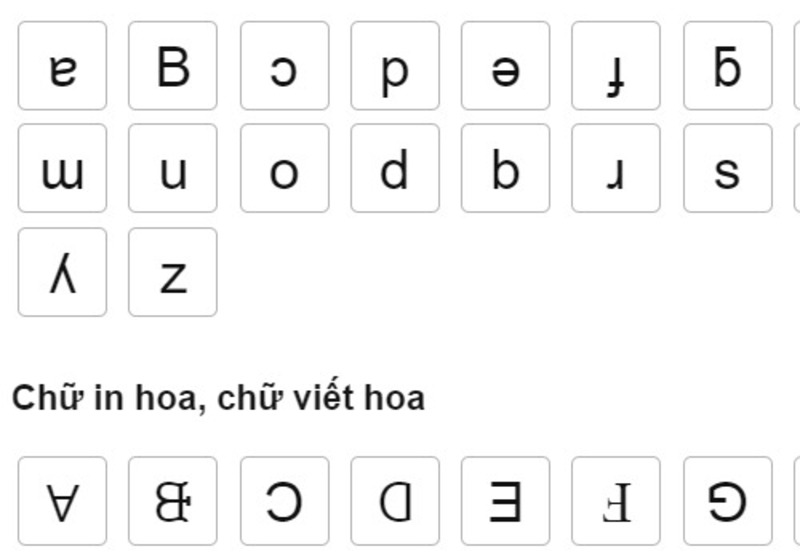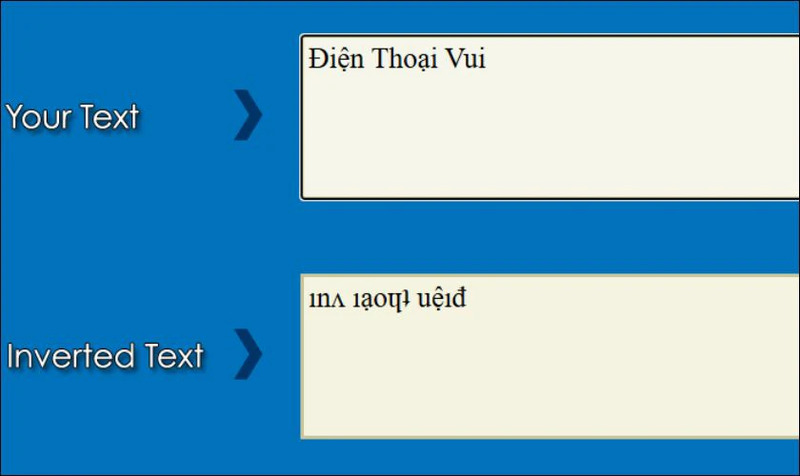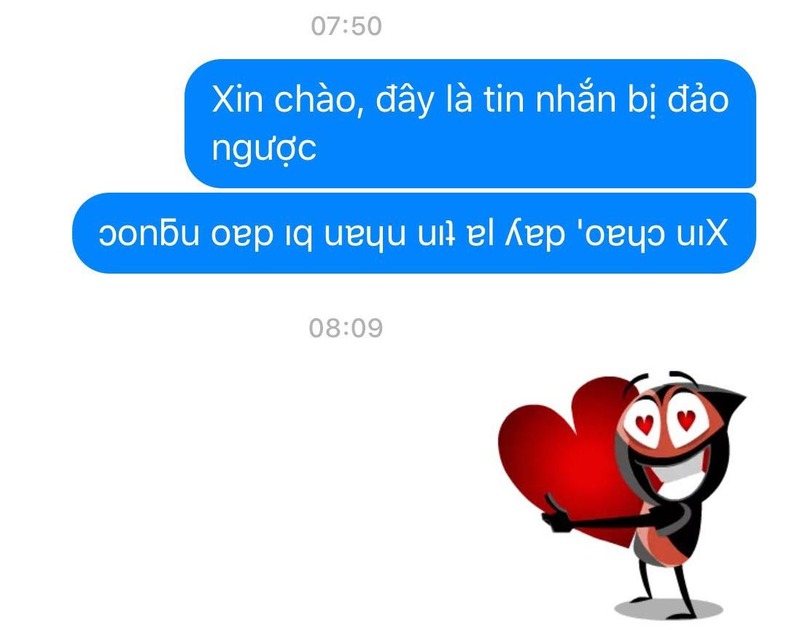
Chữ ngược là kiểu chữ tạo ra những văn bản có hình dạng đảo ngược hoặc xoay lộn so với cách viết thông thường. Nội dung sau sẽ giúp bạn hiểu rõ về khái niệm chữ ngược, các ứng dụng thực tế của chữ đảo ngược trong cuộc sống số, hướng dẫn cách tạo chữ viết ngược bằng công cụ Mobifonts, cũng như giải đáp những thắc mắc phổ biến về ký tự chữ ngược. Từ việc sử dụng trên mạng xã hội, đặt tên trong game, thiết kế đồ họa cho đến các mục đích bảo mật, ký tự chữ v ngược và các ký tự đặc biệt chữ ngược khác đang mở ra một thế giới sáng tạo hoàn toàn mới.
Chữ ngược là những ký tự được tạo ra bằng cách đảo ngược, xoay lộn hoặc biến đổi hình dạng của các chữ cái thông thường để tạo ra hiệu ứng thị giác độc đáo. Các ký tự này thường được tạo ra thông qua việc sử dụng Unicode và các bộ ký tự đặc biệt, giúp văn bản trở nên khác lạ và thu hút sự chú ý.
Một số ví dụ phổ biến về chữ ngược bao gồm việc viết các chữ cái Latin theo chiều ngược lại, sử dụng các ký tự Unicode đặc biệt để tạo hiệu ứng gương, hoặc áp dụng các thuật toán đảo ngược chuỗi ký tự. Những ứng dụng này không chỉ mang tính giải trí mà còn có thể được sử dụng trong các mục đích chuyên môn như thiết kế đồ họa, bảo mật thông tin, hay tạo các hiệu ứng thị giác đặc biệt.
Về bản chất, chữ ngược không phải là một ngôn ngữ riêng biệt mà là cách thức trình bày văn bản với hình thức thị giác khác thường. Điều này được thực hiện thông qua việc áp dụng các thuật toán chuyển đổi ký tự hoặc sử dụng các font chữ đặc biệt. Khi sử dụng chữ ngược, người dùng có thể tạo ra những dòng text có thể đọc từ phải sang trái, từ dưới lên trên, hoặc có hình dạng lộn ngược hoàn toàn.
Chữ ngược được sử dụng phổ biến trên các mạng xã hội như Facebook, TikTok để gây chú ý, cho đến đặt tên ingame hoặc gửi tin nhắn lạ mắt trong trò chơi. Cùng tham khảo chi tiết ngay dưới đây:
Trên các nền tảng mạng xã hội như Facebook, Instagram, TikTok hay Twitter, viết chữ ngược đã trở thành một xu hướng phổ biến để tạo sự thu hút và khác biệt. Người dùng thường sử dụng chữ ngược trong cá nhân, caption của bài đăng, hoặc trong các bình luận để tạo ra sự chú ý đặc biệt.
Việc sử dụng chữ đảo ngược trên mạng xã hội không chỉ giúp nội dung trở nên độc đáo mà còn có thể tăng tương tác từ người theo dõi. Nhiều nhà sáng tạo nội dung đã tận dụng chữ ngược để tạo ra những bài đăng viral, thu hút sự tò mò của cộng đồng mạng. Điều này đặc biệt hiệu quả trong việc xây dựng thương hiệu cá nhân và tạo ra dấu ấn riêng biệt.
Trong thế giới game, chữ viết ngược đã trở thành một phần không thể thiếu trong văn hóa đặt tên nhân vật và giao tiếp. Nhiều game thủ sử dụng chữ ngược để tạo ra những tên nhân vật độc đáo, khó quên và thể hiện cá tính riêng biệt trong cộng đồng game. Việc sử dụng ký tự chữ ngược trong game không chỉ mang tính thẩm mỹ mà còn có thể có tác dụng chiến thuật. Một số game thủ chuyên nghiệp sử dụng chữ ngược để tạo ra các tên nhân vật khó đoán, giúp họ ẩn danh trong các trận đấu quan trọng hoặc tránh bị theo dõi bởi đối thủ. Dưới đây là một số ví dụ tiêu biểu:
Faker (Liên Minh Huyền Thoại) => RəʞɐℲ
Levi (GAM Esports – LMHT) => iʌǝ⅃
Box Gaming (PUBG Mobile) => ɯɐƃ ɯoɐq
Trong hệ thống chat của game, ký tự chữ v ngược và các ký tự đặc biệt khác cũng được sử dụng để tạo ra những tin nhắn thú vị, mã hóa thông tin hoặc đơn giản là để tạo sự khác biệt trong cách giao tiếp. Nhiều cộng đồng game đã phát triển cả một "ngôn ngữ" riêng dựa trên chữ ngược để giao tiếp nội bộ.
Trong lĩnh vực thiết kế đồ họa, chữ ngược được ứng dụng như một kỹ thuật nghệ thuật để tạo ra những hiệu ứng thị giác độc đáo và thu hút. Các nhà thiết kế sử dụng ký tự đặc biệt chữ ngược để phá vỡ quy tắc kiểu chữ truyền thống, tạo ra những tác phẩm sáng tạo và ấn tượng. Ví dụ:
Thương hiệu giày "ƃuᴉɥɔʇɐɯ" (matching)
Giao diện ứng dụng thời tiết "ƃuᴉuɐɯ ɹɐǝʍ" (wearing rain)
Logo thương hiệu thời trang đường phố “ƎPIƎC” (Tên thật: EPIC)
Việc áp dụng chữ ngược trong thiết kế có thể tạo ra cảm giác bí ẩn, hiện đại hoặc mang phong cách tương lai cho các sản phẩm thiết kế. Từ áp phích, logo cho đến các thiết kế web, chữ đảo ngược đã trở thành một công cụ mạnh mẽ giúp các nhà thiết kế thể hiện ý tưởng sáng tạo và tạo ra sự khác biệt trong thị trường cạnh tranh.
Một ứng dụng ít được biết đến nhưng rất quan trọng của chữ ngược là trong lĩnh vực bảo mật thông tin. Viết chữ ngược có thể được sử dụng như một phương pháp mã hóa đơn giản, giúp che giấu thông tin nhạy cảm khỏi những người không được phép truy cập. Những ví dụ cụ thể như:
Ẩn nội dung keyword nhạy cảm để tránh bị kiểm duyệt AI / thuật toán. Thay vì viết: “Hack tool”, người dùng có thể viết thành → ʞɔɐH looʇ hoặc ɥɐɔʞ ʇool
Game thủ dùng tên đảo để tránh bị tìm ID hoặc truy vết. Một người chơi rank cao trong Valorant tên là “HunterPro” sẽ đổi thành→ orPerʇuɥ hoặc ɹoԀ ɹǝʇuɥ
Chữ ngược đã trở thành một phần không thể thiếu trong văn hóa số hiện đại, mang lại những giá trị độc đáo từ giải trí đến ứng dụng chuyên nghiệp. Qua bài viết này, chúng ta đã khám phá được tính đa dạng và phong phú của viết chữ ngược, từ việc sử dụng trên mạng xã hội, trong gaming, thiết kế đồ họa cho đến các mục đích bảo mật. Với sự phát triển không ngừng của công nghệ và nhu cầu thể hiện cá tính ngày càng cao, ký tự chữ ngược, ký tự chữ ngược và các ký tự đặc biệt chữ ngược khác chắc chắn sẽ tiếp tục đóng vai trò quan trọng trong cách chúng ta giao tiếp và sáng tạo trong thế giới số.